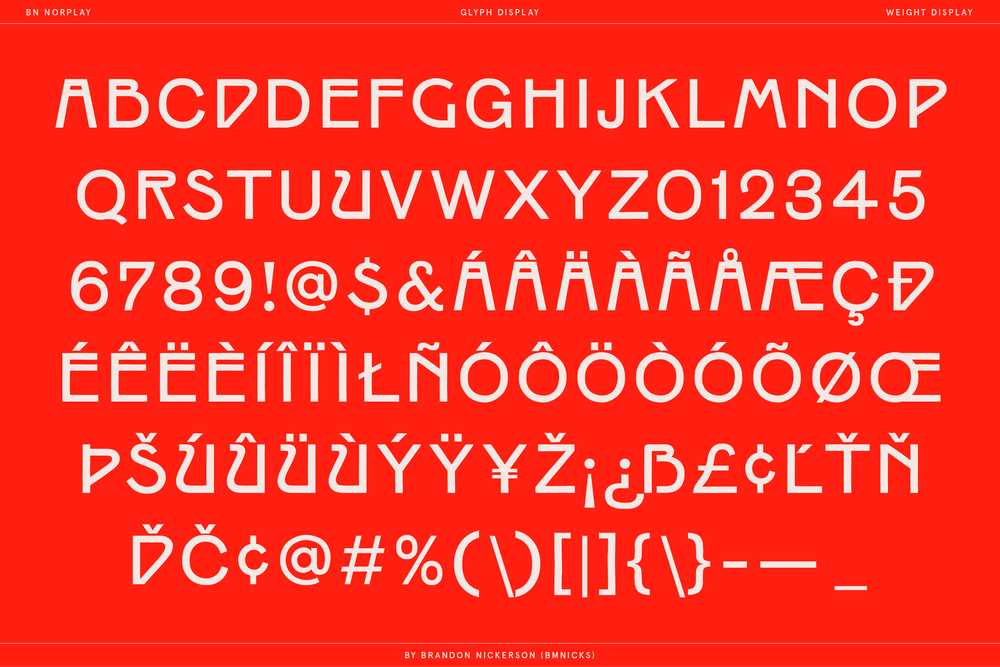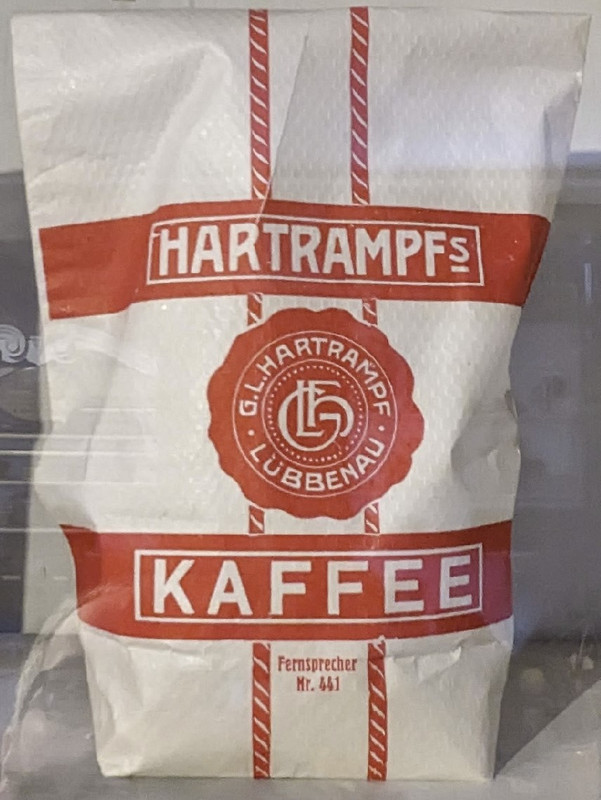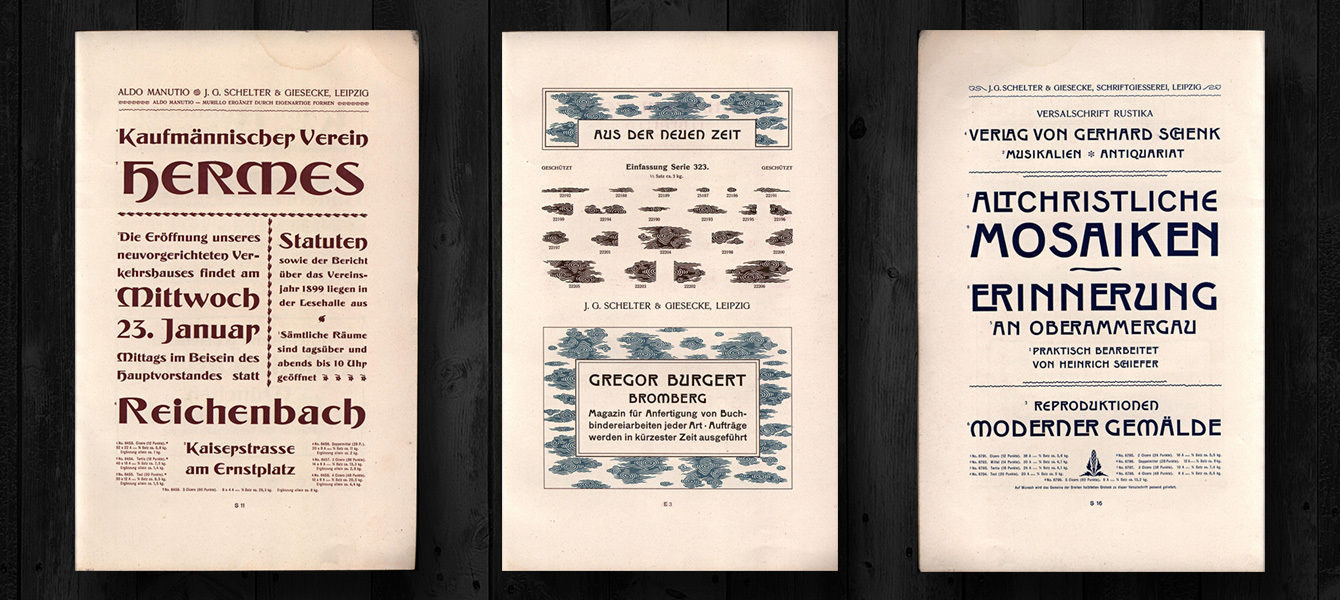
Suche serifenlose Schrift ~1900
Hallo, ich bin auf der Suche nach einer Serifenlosen, ähnlich wie die Schrift im Anhang. Soll so an Schriften aus 1880–1920 erinnern, würde mich da aber zeitlich nicht so festlegen. Wichtig ist eher das R mit dem schrägen Bogen, gern auch beim Mittelstrich von A, H ... serifenlos oder kleine Serifen wie Brothers (Emigre) jeder Vorschlag ist gern gesehen.
WF Wittelsbach hat ein schräges R. Die anderen Schriften in meinem Art Nouveau Printshop haben auch ähnliche Formen, und alle passen in den von Dir angegebenen Zeitraum.
Mir ist gestern auch etwas ähnliches über den Weg gelaufen:
Norplay von Brandon Nickerson geht auch in die Richtung, wenn auch das R etwas anders ist.
Die Rustika war auf meiner kurzen Liste. Am Ende entschied ich mich dann aber für die Rienzi Versalien.
ja, die gehören zusammen, Rustika ist sozusagen die fette Version der Rienzi. Die Norplay hat mehrere Schnitte und der Light kommt der Rienzi nahe. Deine Digitalisierung ist aber liebevoller, die Norplay ist etwas rough im Strich und imitiert eher die gepressten Lettern. Außerdem hat Deine Version die ganzen schicken Ligaturen aus dem Original. Wenn Du eine fette Rustika nachliefern würdest, fänd ich das richtig cool und würde zuschlagen!